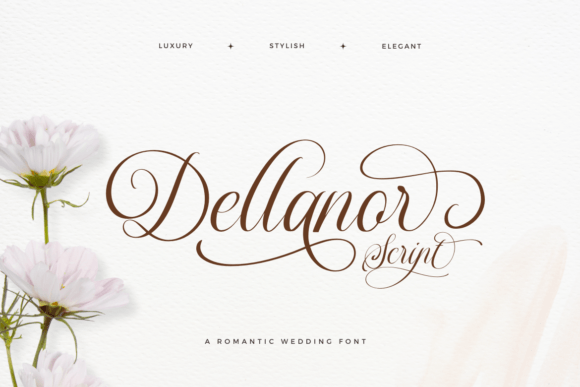
Dellanor Script
Dellanor Scriptのような高品質の素材をお探しの場合、このプレミアムパッケージはクリエイティブなプロジェクトに素晴らしい選択です。
精密に作られたDellanor Scriptは、クリーンなベクター、滑らかなタイポグラフィ、そして安心のための商用ライセンスを提供します。
POD(オンデマンド印刷)製品、結婚式の招待状、またはソーシャルメディアのグラフィックを作成している場合でも、Dellanor Scriptは理想的です。